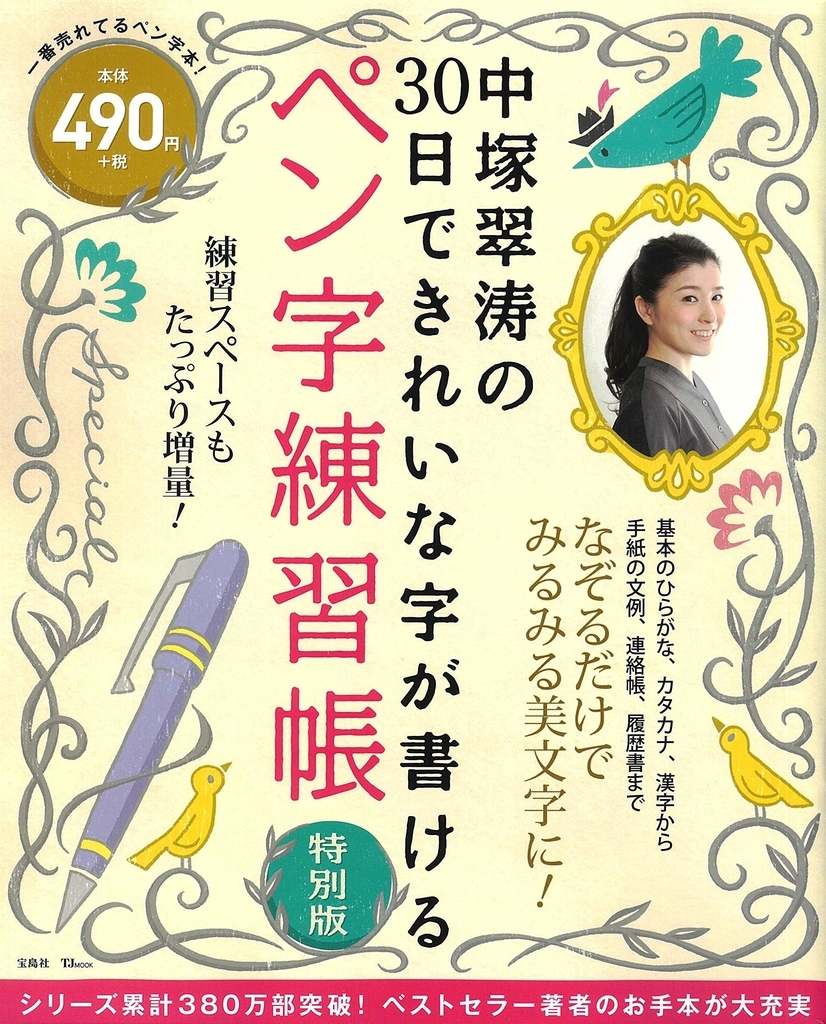
中塚翠涛の30日できれいな字が書けるペン字練習帳 特別版
宝島社から2018年12月25日に1日2ページ、忙しい社会人でも始めやすく、伝言メモや履歴書など、横書きも練習でき、大人字、サインペン・筆ペンの文字など用途別でも使えるムック本「中塚翠涛の30日できれいな字が書けるペン字練習帳 特別版」が発売された。
「中塚翠涛の30日できれいな字が書けるペン字練習帳 特別版」は、「美文字ブーム」の火付け役として、テレビや雑誌などでも活躍中の書家・中塚翠涛氏が監修・手本を手がけるペン字練習帳シリーズの最新刊。
本シリーズは、なぞり書きから練習できるスタイルが特徴で、30~40代の女性を中心に幅広い層から支持を得てシリーズ累計390万部突破した、ネット社会の今でも手書きの機会が多い各種届出書類やお祝いメッセージ、宅配便の伝票からビジネスでのちょっとした伝言メモまで、幅広いシーンで使える、文字を美しく書くためのコツとポイントがおさえられたシリーズ。
今回はシリーズ10冊目を記念した「特別版」として、これまでのシリーズで反響の大きかった内容を厳選して再収録した。
中塚翠涛Profile●岡山県倉敷市出身。東京都在住。4歳から書に親しむ。古典的な書をもとに、和紙、陶器やガラス、映像などの様々な手法で、文字の持つ魅力を表現し、国内外で活動。創作活動と同時に、多くの方に手書きを楽しんでもらいたいという想いから、ペン字練習帳等の出版も多数。『中居正広の身になる図書館』(テレビ朝日)をはじめ、多くのテレビ番組や雑誌で活躍。
職場や冠婚葬祭の場で字を書くときに、もっときれいに書けたら、と思ったことが誰でも一度はあるはずです。
書家・中塚翠涛先生が30日できれいな字が書けるレッスンをまとめました。
練習は1日2ページ。自宅やすき間時間をつかって気軽に練習ができるので、忙しい社会人でも始めやすいのがポイント。
すべて20~30分以内で終わるので、ちょっとした時間でも取り組みやすく、気負わず練習することができます。
基本の「楷書」はもちろん、文字をつなげて書く「大人字」、さらに「サインペン書き」「筆ペン書き」まで、
これ一冊にさまざまな練習を盛り込んだ特別版です。